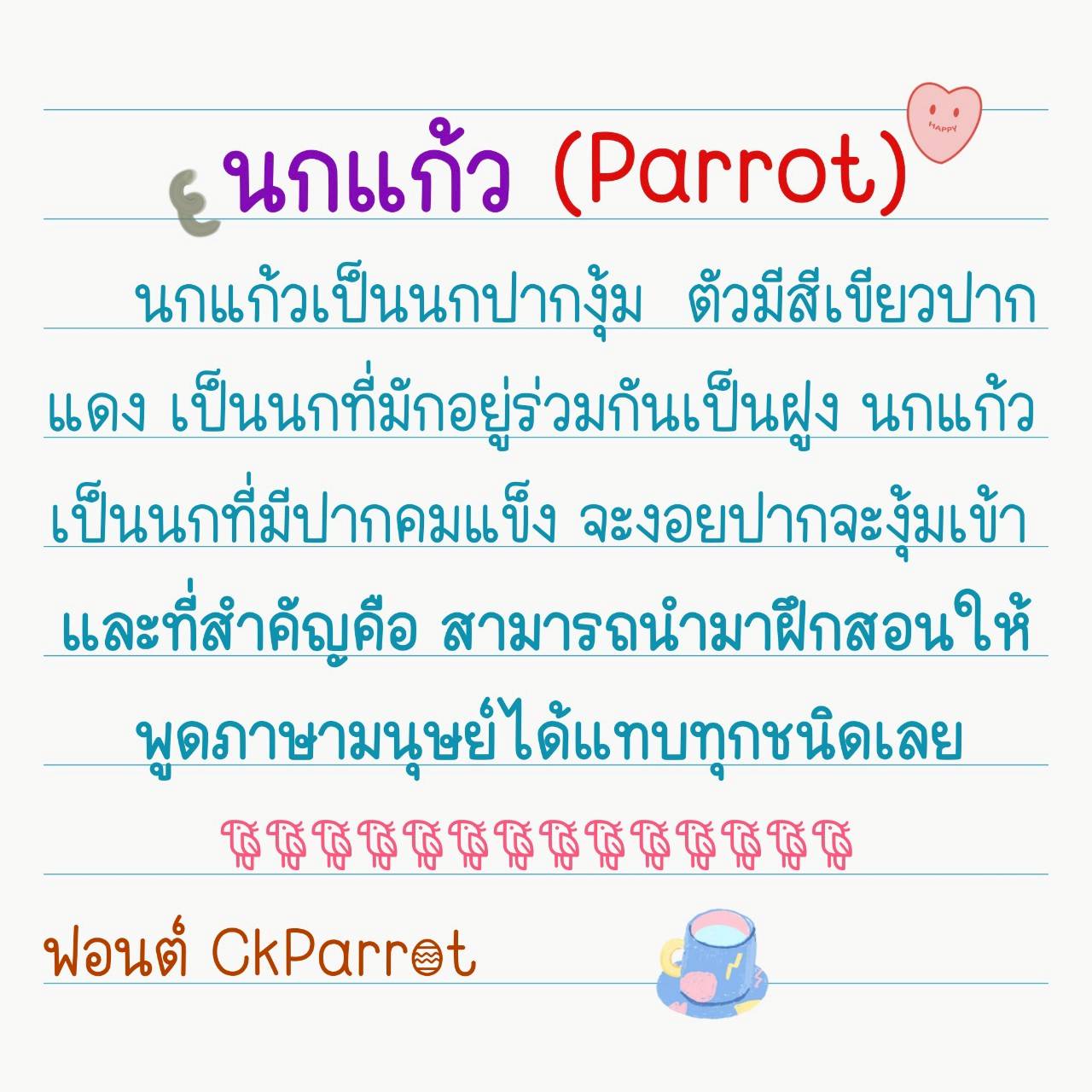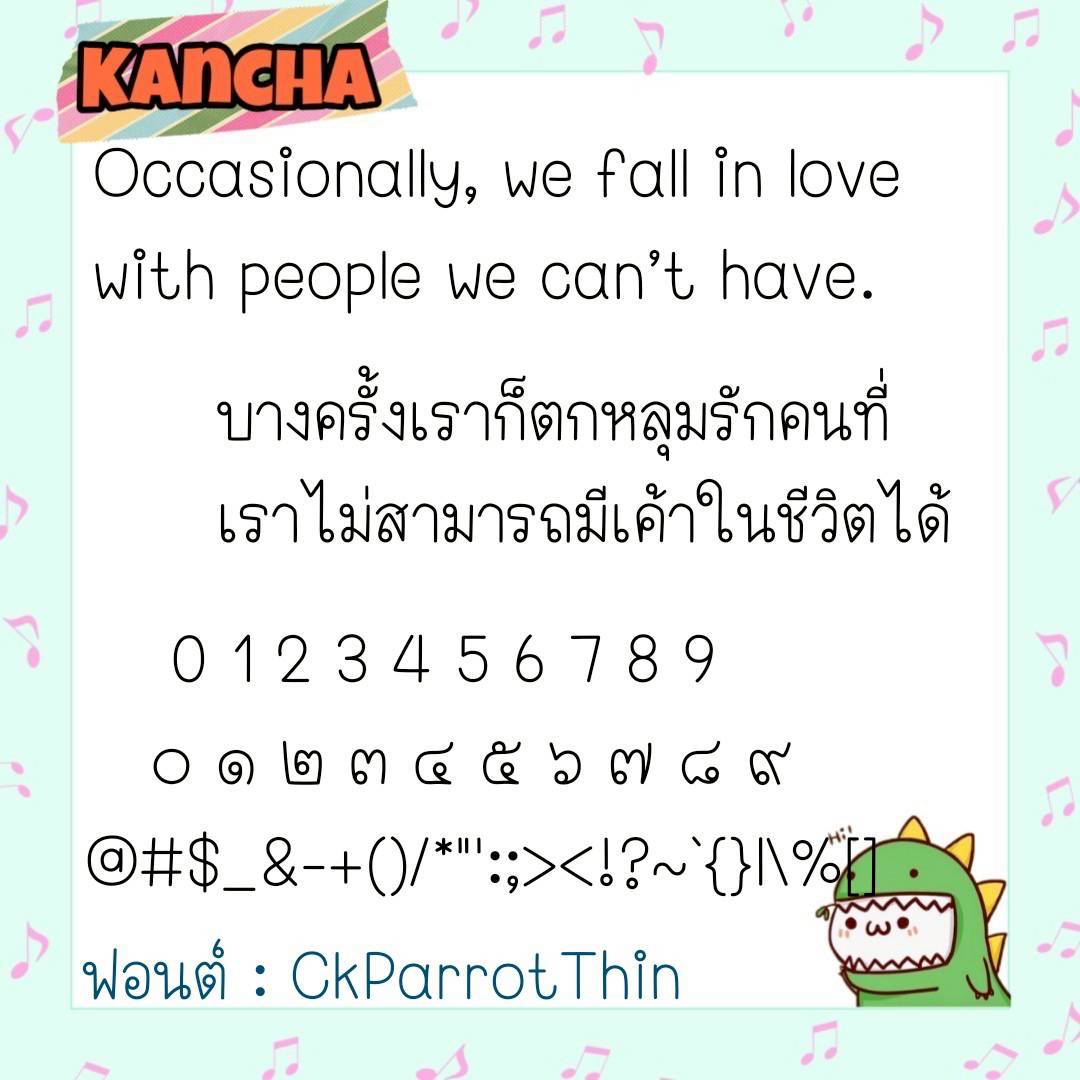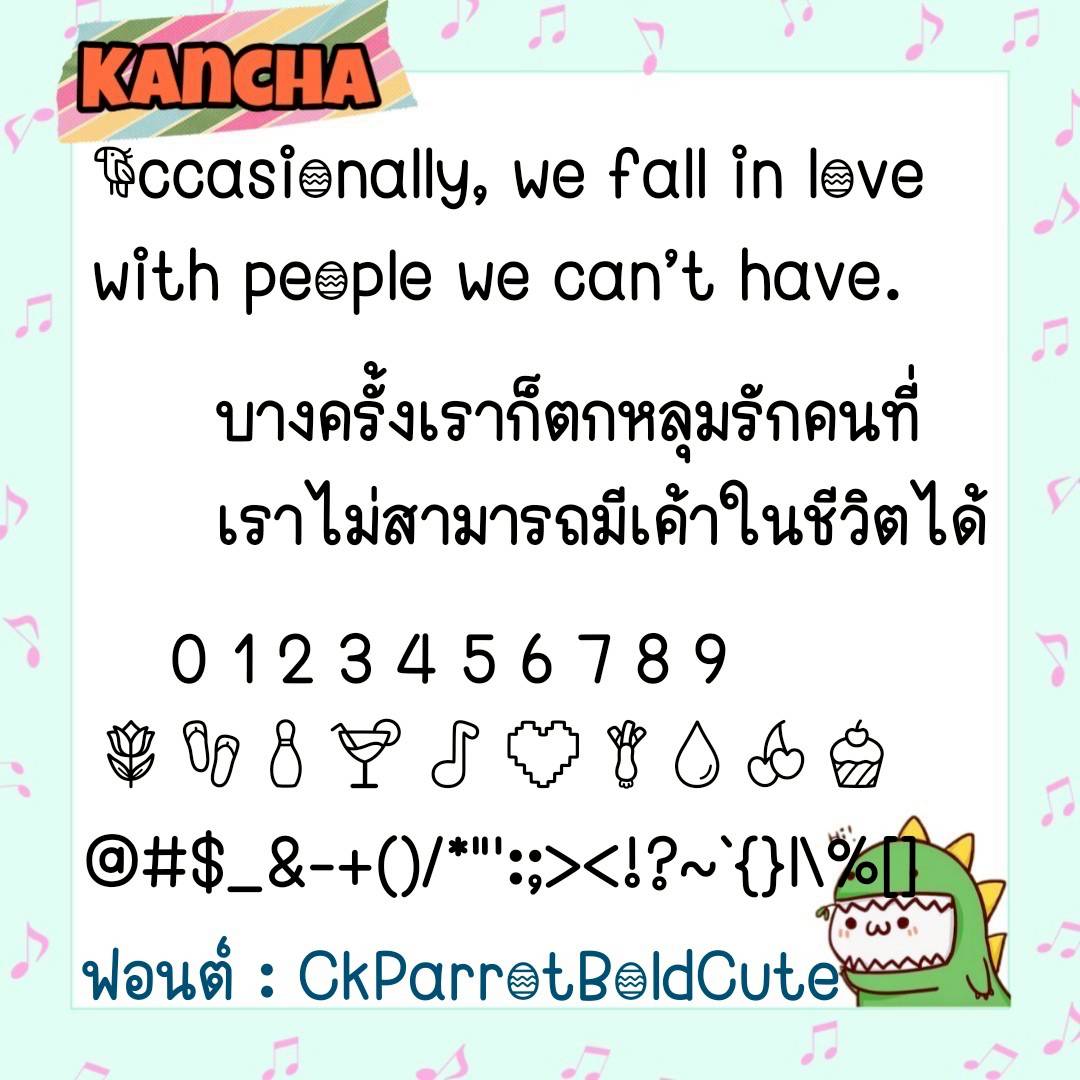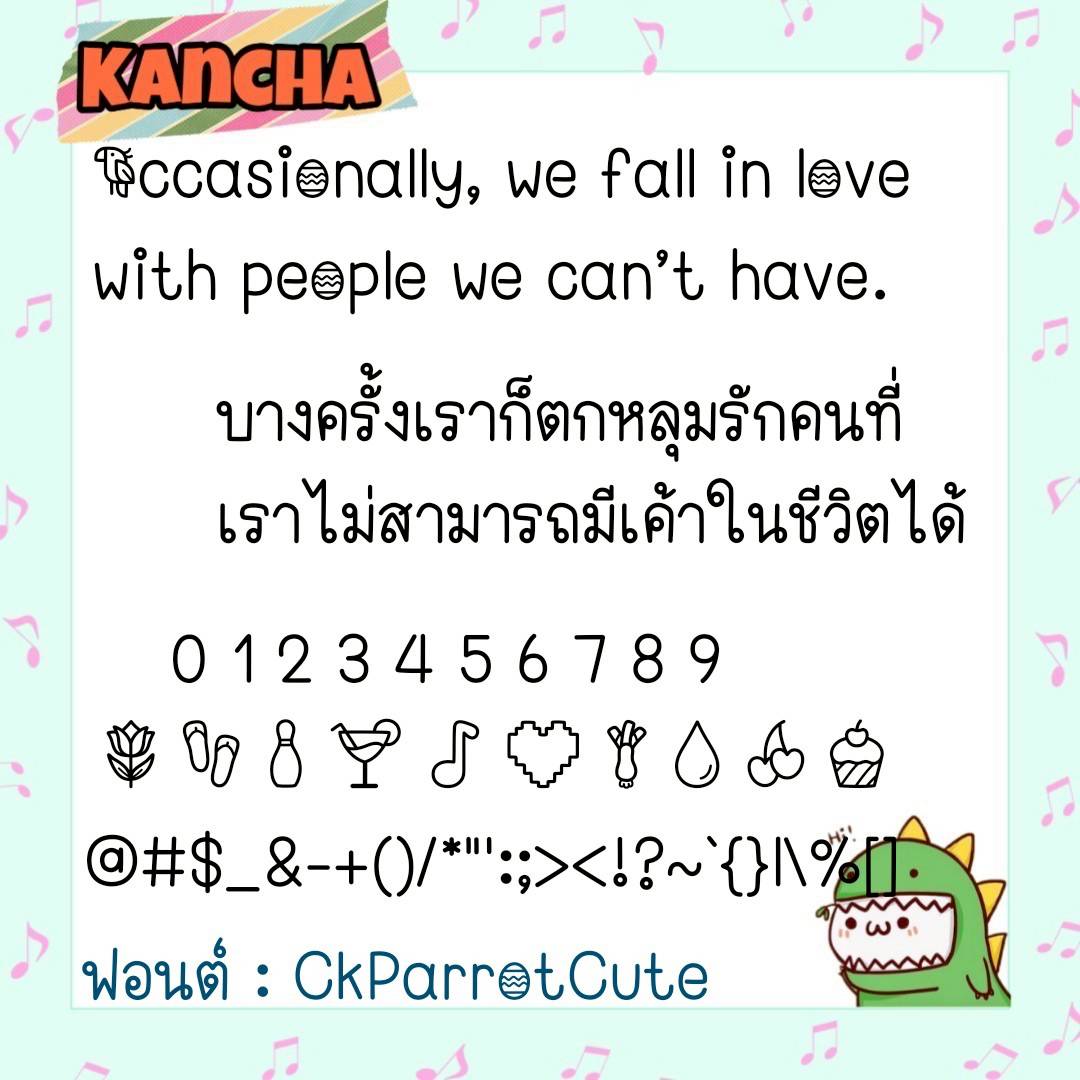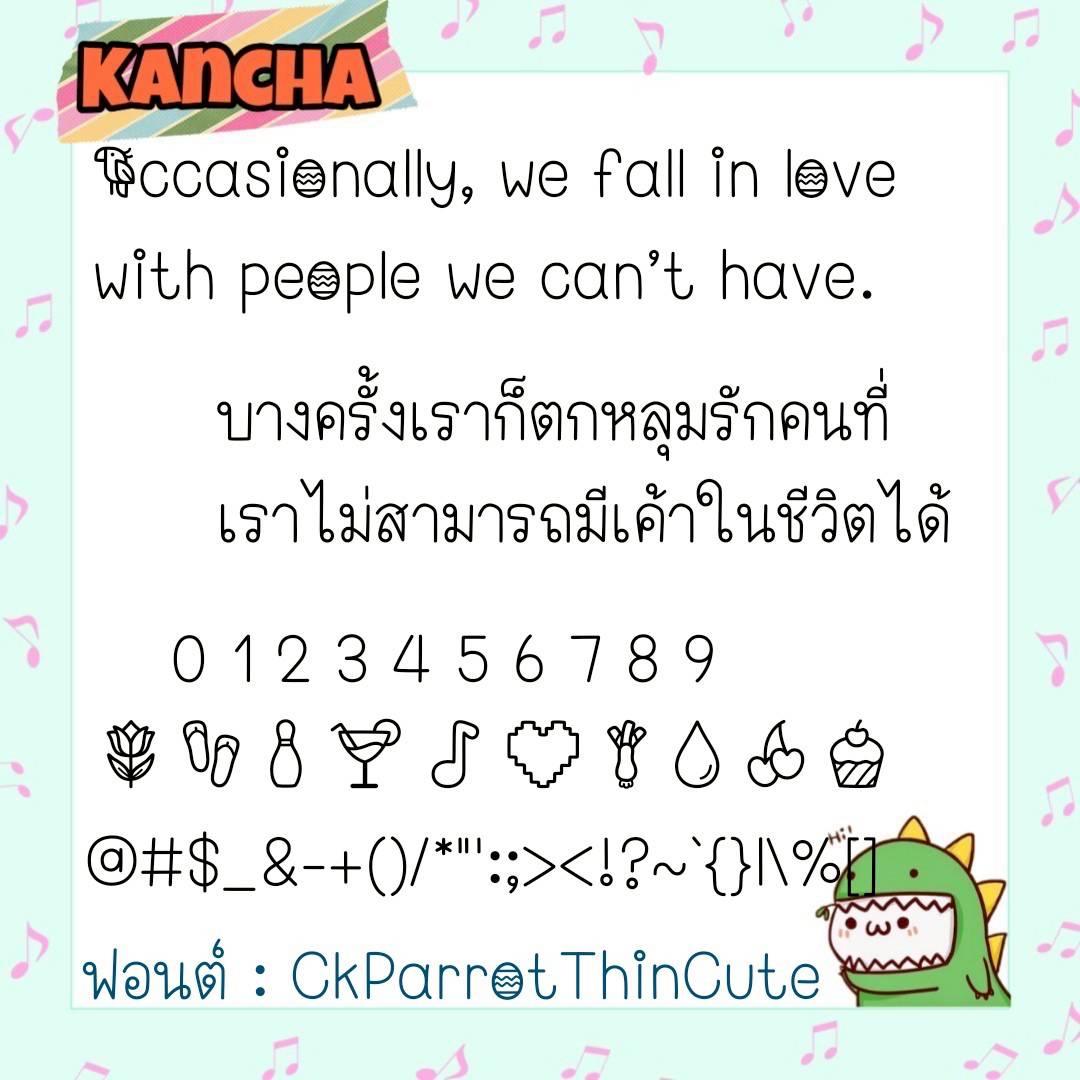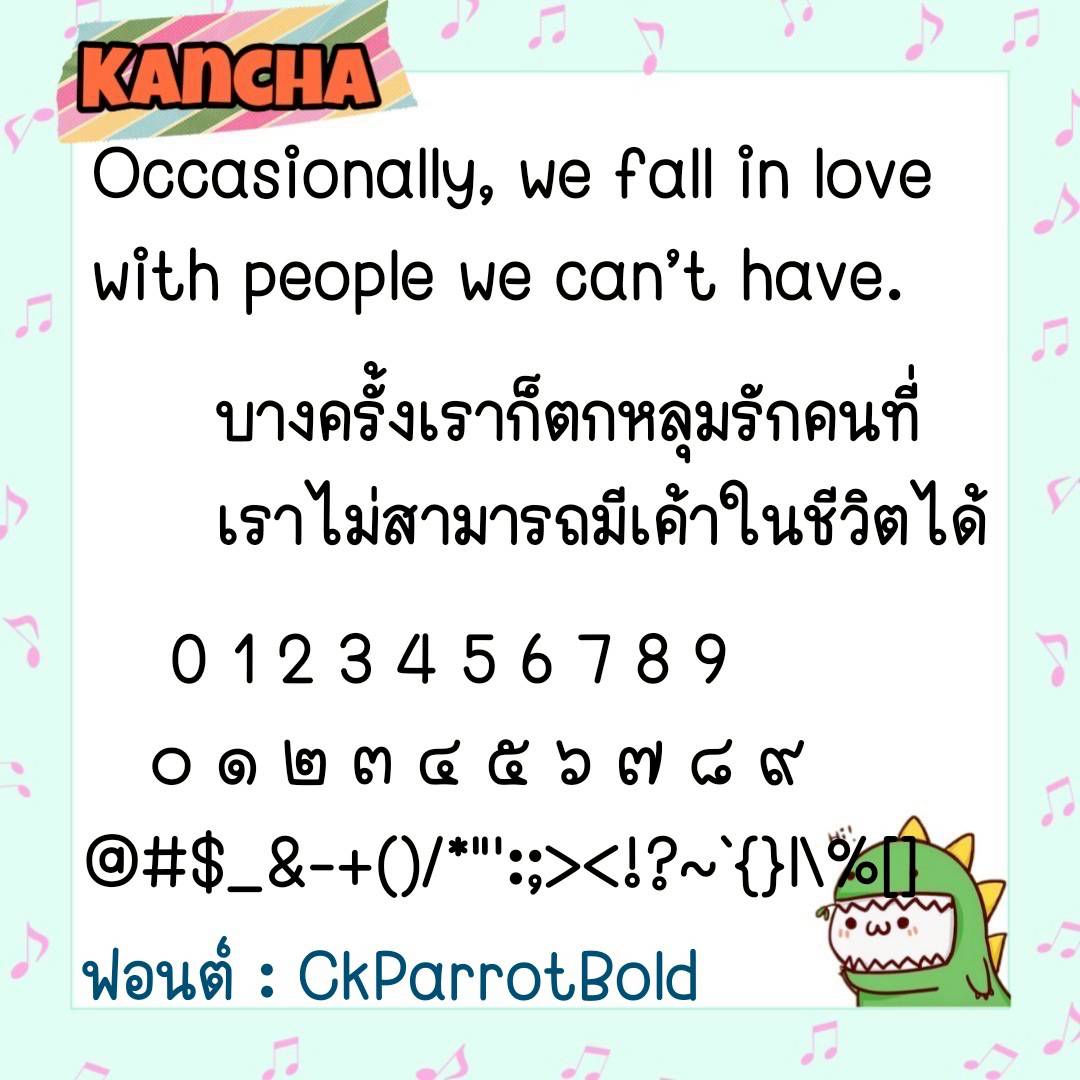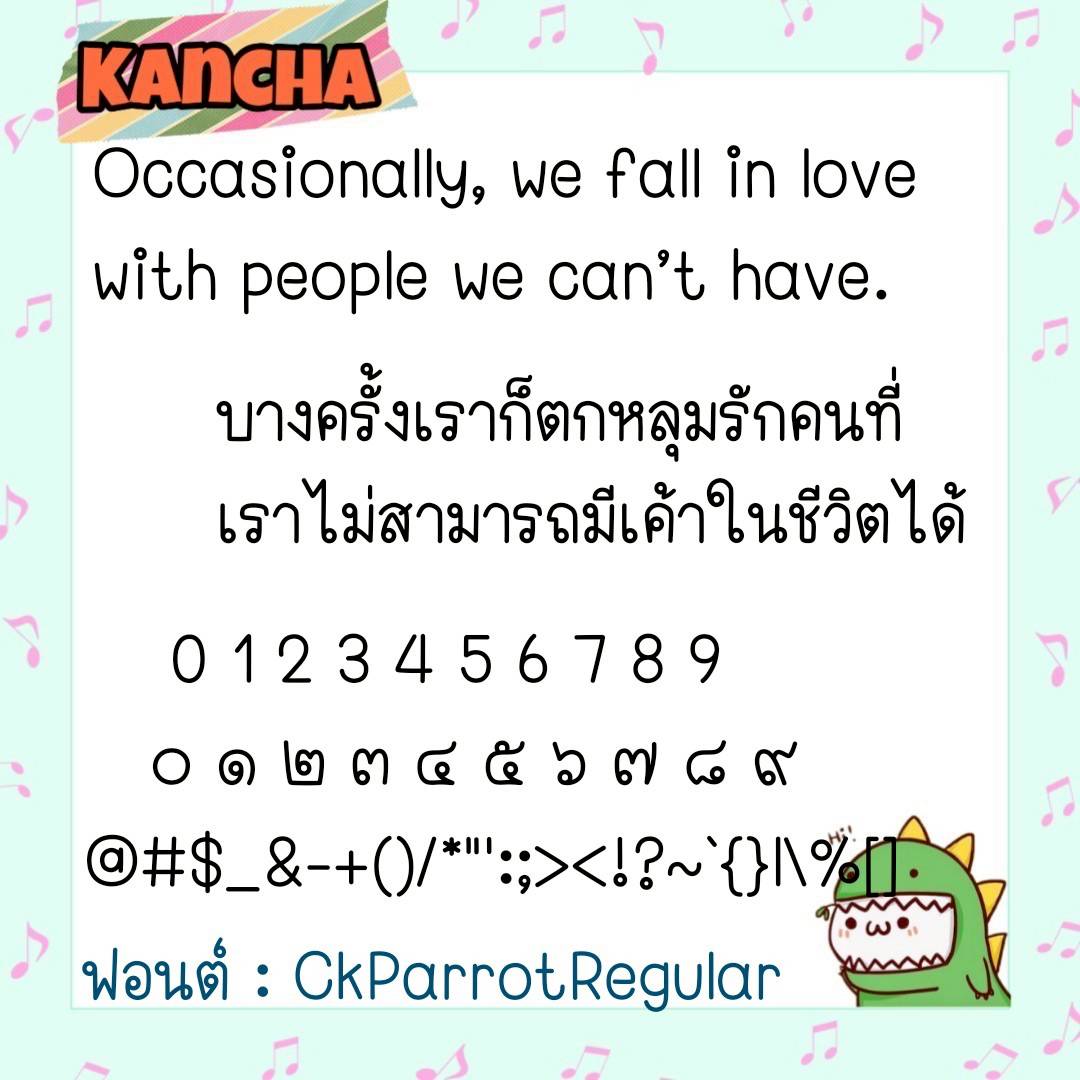
Font CkParrot
🔸 ฟอนต์ลายมือแนวเรียบร้อย มีความกึ่งเหลี่ยมกึ่งเป็นระเบียบแบบไทยๆ แต่ก็ยังดูมีความน่ารัก อ่านง่ายสบายตาอยู่ในตัว และยังมีไฟล์อิโมจิน่ารักๆ ที่ใช้แทนเลขไทยให้ด้วยค่ะ 🥰💙
🔹 The font is handwritten in a neat style, with a semi-square, semi-orderly Thai style, but it still looks cute, easy to read, and comfortable to the eyes. There is also a file of cute emojis that can be used to replace Thai numbers. 🥰💙